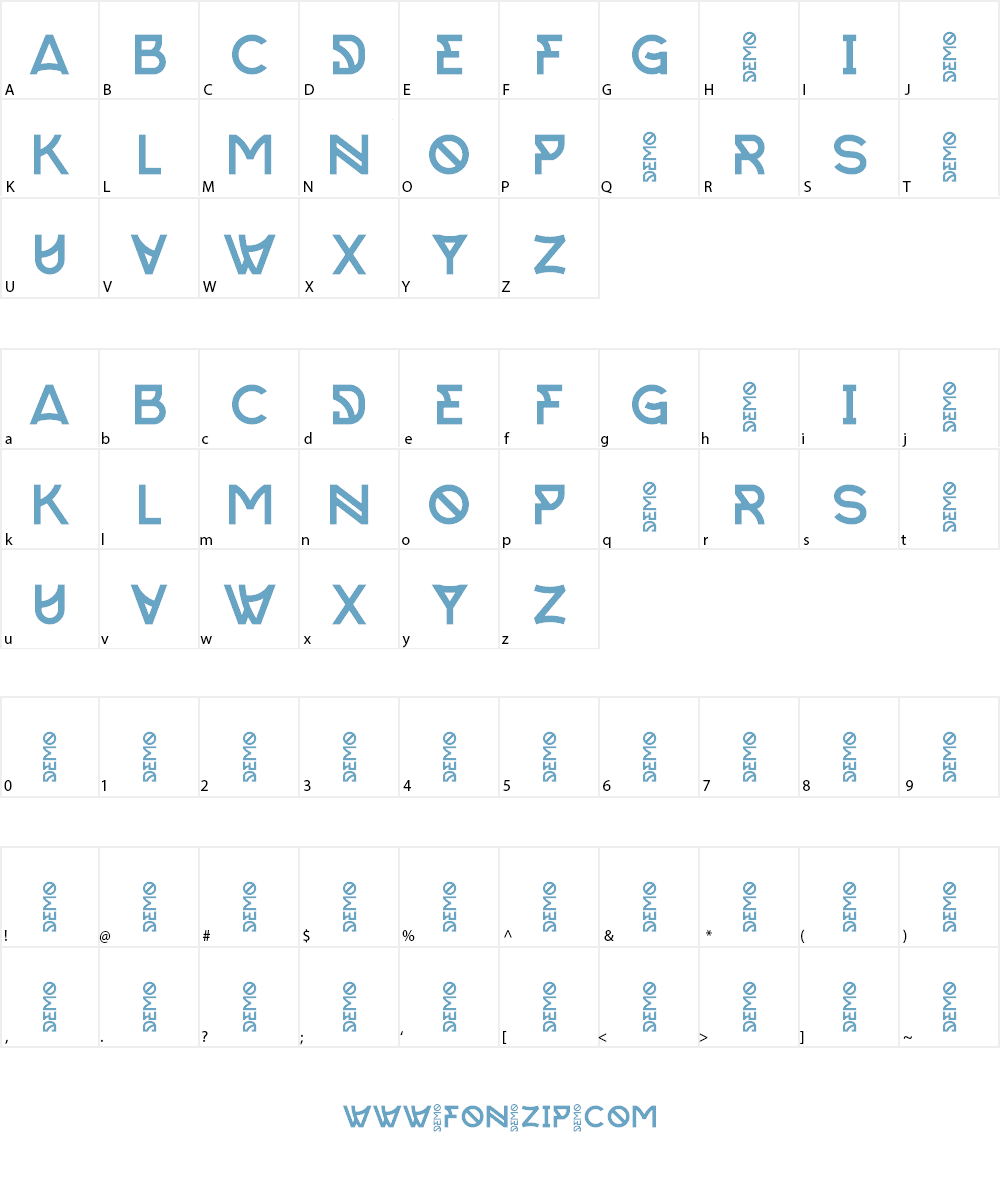
ZILAP SOUND TYPEFACE - Diseñada por Zilap Estudio, la fuente es contemporánea y geométrica con un estilo urbano y futurista, el enfoque y concepto esta basado en la música con un diseño simple y funcional, para que encaje en todo tipo de proyectos visuales.